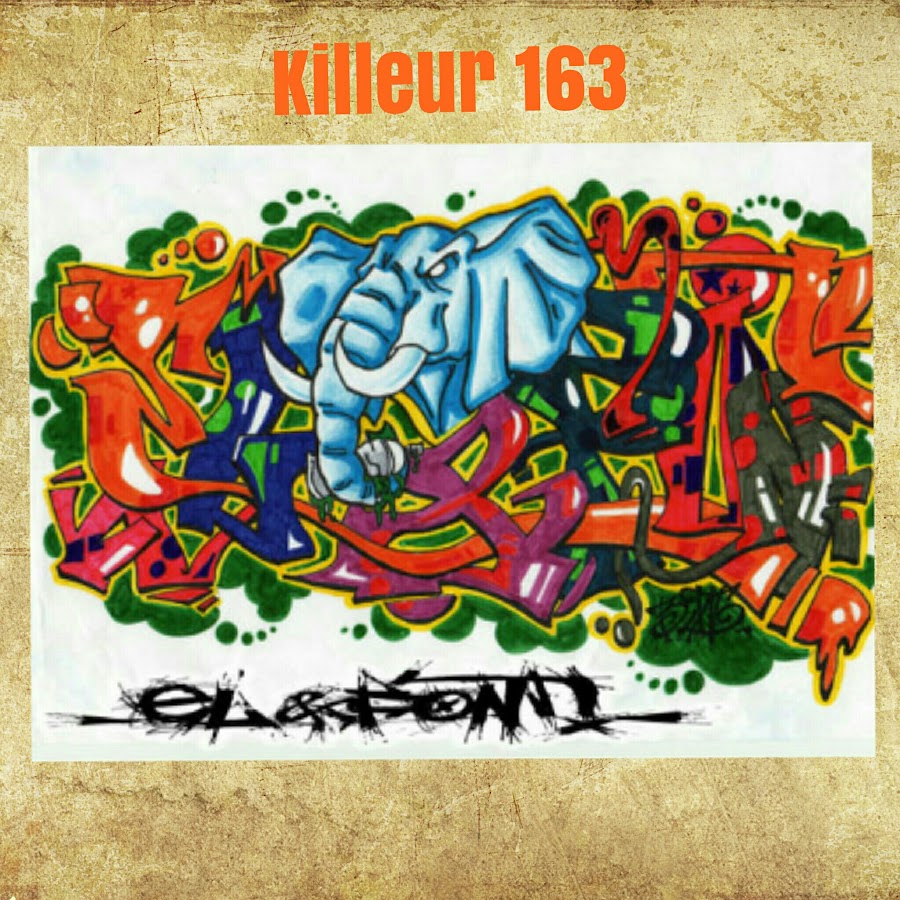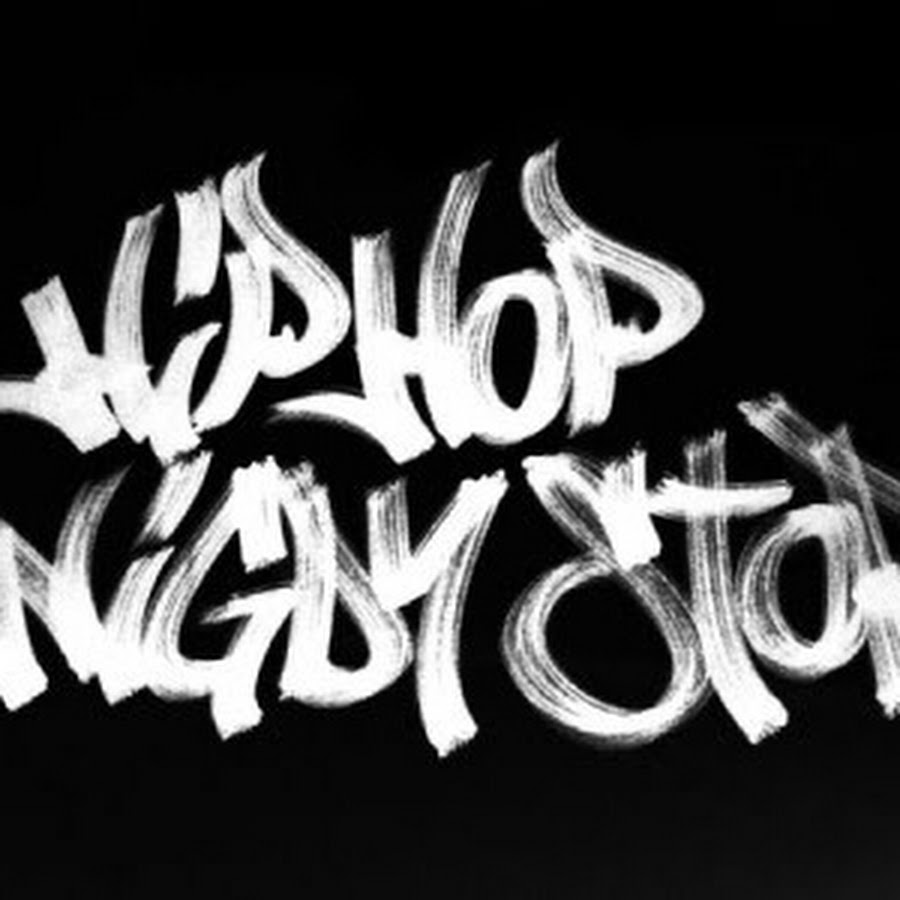
111 бесплатных граффити шрифтов на все случаи жизни | Canva
Граффити можно уверенно назвать одним из самых древних и долговечных видов искусства – первые наскальные рисунки были сделаны много тысячелетий назад, когда древние люди научились расписывать свои пещеры. С тех пор граффити художники сильно развили свои навыки.
Мы собрали 111 граффити шрифтов, большинство из которых доступны и на русском и английском языках, и все без исключения можно скачать бесплатно. Выражайте дух улиц в любом дизайне свободно и с удовольствием!
ачинаем подборку с граффити шрифтов, доступных только на английском языке. Здесь есть и классика уличной культуры, и креативные, современные, авторские шрифты, которые вас удивят.
1. Ruthless Wreckin ONE
Один из самых впечатляющих граффити шрифтов, который используется абсолютно в разных областях искусства, но при этом всегда несет в себе «уличную» эстетику.
2. HumgerЭто гранжевый шрифт с текстурой в винтажном стиле. В его дизайне чувствуется большое влияние старомодных шрифтов-трафаретов. Шрифт доступен бесплатно и для личного, и для коммерческого использования.
3.Это очень популярный шрифт граффити, имеющий некий уклон в олд-скул. Буквы здесь хорошо различимые, но имеют много интересных «заковык», которые придают ему уникальности.
4. BlackTopВ этом стильном рукописном граффити шрифте есть еще и прикольные бонусные элементы. Корона, алмаз или звездочка могут добавить творческую нотку вашему дизайну.
5. MarsnevenekskОдин из самых распространенных и любимых шрифтов граффити художников. Относится к главному виду граффити под названием «writing» т.е. здесь фокус на буквах и их дизайне.
6. The Graffiti FontА это пример знаменитого стиля граффити «bubble». Его главная особенность – округлая форма букв и простота рисунка. В процессе создания авторы чаще всего используют два цвета: первый для заполнения внутреннего пространства букв, а второй для нанесения контура.
«Bombing» – это не только название шрифта, но и всего направления уличного искусства: именно этот вид нанесения граффити был самым используемым в 70-80-х годах. Изначально «бомбили» в основном поезда, но сейчас этот термин применим и к другим местам. Суть «бомбинга» в быстро-созданном рисунке на видном месте.
8. Don GraffitiОлдскульный граффити шрифт, в котором четко читается урбанистический характер. Здесь есть разрывы в плавных линиях некоторых букв, делающие шрифт необычным и креативным.
9. PainterzЭтот шрифт стилизован под граффити, нанесенные баллоном. Здесь буквы стоят вплотную друг к другу, а в самом шрифте есть элементы, которые имитируют характерное распыление краски при пользовании баллончиком.
10. Marker No2HunУверенный и дерзкий стиль такой надписи создается маркером. Обведенные по несколько раз буквы создают ощущение легкой небрежности художника, тем не менее четко знающего свое дело.
11. Detroit GhettoАвтор рассказывает, что на создание этого шрифта его вдохновила прогулка по трущобам Ист Сайта в Детройте, штат Мичиган, США. Такие вот «пляшущие» буквы подарили нам уличные художники Детройта.
12. Scare ArmsЭтот вариант идеален для тех, кому нужна пугающая надпись. Шрифт сделан в стиле ужасов, с колючим и размытым внешним видом.
13. Grizzly AttackЕще один креативный шрифт в продолжение темы ужасов. Если бы медведь гризли рисовал надпись на стене своими когтями – это выглядело бы примерно так.
14. BRUXПо словам автора Brux, художника из Стокгольма, – этот стильный, смелый и живой граффити шрифт имеет шведский, немецкий и испанский характер.
15. Gang Bang CrimeЕще один пример шрифта граффити в стиле «Bombing».
Крупные уверенные буквы и потеки краски будто выражают неподчинение системе, риск и решительность.
16. StreetwearЭто стильный граффити шрифт в стиле ретро, подходящий для логотипов, плакатов и брендинга. В нем читаются элементы спортивной моды 1960-х и 70-х годов, поэтому также можно использовать в дизайне одежды, например, футболок.